برای طراحی و یا ادیت مذهبی، بهترین فونت های فارسی مذهبی کداماند؟
تا به حال برایتان پیش آمده که بخواهید یک پوستر برای ایام شهادت، میلاد ائمه یا مناسبتهای مذهبی طراحی کنید، اما هرچقدر فونتهای مختلف را امتحان میکنید، آن حس “معنویت و وقار” در کار دیده نمیشود؟ انگار یک جای کار میلنگد. طرح شما ممکن است از نظر تکنیکی بینقص باشد، اما اگر فونت انتخابی با محتوای مذهبی همخوانی نداشته باشد، پیام شما به دل مخاطب نمینشیند.
در دنیای طراحی گرافیک، انتخاب فونت برای کارهای مذهبی، چیزی فراتر از چیدمان حروف است؛ این کار، نوعی “خوشنویسی مدرن” است که باید بتواند احترام، عظمت و آرامش را به مخاطب منتقل کند. استفاده از یک فونت فانتزی یا بسیار مدرن در یک اطلاعیه هیئت یا پوستر مذهبی، میتواند تضاد آزاردهندهای ایجاد کند.
در این مقاله از سایت دیاکوگرافیک، قصد داریم راز انتخاب هوشمندانه فونت برای کارهای مذهبی را فاش کنیم و بهترین فونتهای فارسی مذهبی را به شما معرفی کنیم تا دیگر نگران “ناقص بودن” طرحهایتان نباشید.
چرا فونت مذهبی، روحِ طرح شماست؟
وقتی درباره کارهای مذهبی صحبت میکنیم، مخاطب ما با چشمی به طرح نگاه میکند که به دنبال “احترام” است. فونتهای مذهبی وظیفه دارند این حس را در کسری از ثانیه به بیننده منتقل کنند.
۱. انتقال حس وقار و آرامش
فونتهای مذهبی (مانند نستعلیق، ثلث یا نسخ) بهگونهای طراحی شدهاند که با انحناها و کشیدگیهای خاص خود، حس سنت و اصالت را به همراه دارند. این فونتها به مخاطب میگویند: “این یک پیام جدی و ارزشمند است.”
۲. خوانایی در کنار زیبایی
بزرگترین چالش در طراحی مذهبی، تعادل میان “زیبایی کلاسیک” و “خوانایی مدرن” است. شما نمیخواهید مخاطب برای خواندن متن، انرژی زیادی صرف کند. فونتهای مذهبی استاندارد، این تعادل را رعایت میکنند.
۳. ایجاد هویت بصری برای هیئات و مجموعههای فرهنگی
تکرار یک فونت خاص در تمام پوسترهای یک مجموعه، به مرور زمان تبدیل به هویت بصری آن مجموعه میشود. مخاطبان با دیدن سبک آن فونت، ناخودآگاه نام مجموعه شما را به یاد میآورند.
چگونه بهترین فونتهای مذهبی را در طرحهایمان ترکیب کنیم؟
انتخاب فونت فقط نیمی از مسیر است؛ نیمه دیگر، هنر چیدمان است. بیایید چند گام حرفهای را بررسی کنیم:
گام اول: شناخت جایگاه متن
آیا این فونت برای “تیتر اصلی” است یا “متن بدنه”؟ برای تیترهای مذهبی، همیشه به سراغ فونتهای ضخیم (Bold) یا نستعلیقهای نمایشی بروید. برای متنهای بدنه (مثل آدرس و ساعت هیئت)، فونتهای خوانا و نسخ را انتخاب کنید که چشم مخاطب را خسته نکند.
گام دوم: استفاده از تکنیک کرنینگ (Kerning)
در فونتهای مذهبی، فاصله حروف بسیار اهمیت دارد. اگر فاصله حروف (Kerning) را به درستی تنظیم نکنید، زیبایی فونت از بین میرود. در طراحیهای مذهبی، کمی فضای بیشتر بین حروف، به طرح شما شکوه بیشتری میدهد.
گام سوم: ترکیببندی هوشمندانه
سعی کنید فونتهای مذهبی سنگین (مثل ثلث) را با یک فونت بسیار ساده و مینیمال ترکیب کنید. تضاد بین یک فونت سنتی پرکار و یک فونت مدرن ساده، باعث میشود متن اصلی (مثلاً نام امام یا مناسبت) در طرح شما بدرخشد.
معرفی راهکار تخصصی: چگونه طرحهای مذهبی را متمایز کنیم؟
همه طراحان میدانند که پیدا کردن فونتهای مذهبی که هم “کیفیت بالا” داشته باشند و هم “مجوز استفاده” داشته باشند، کار سختی است. گاهی استفاده از فونتهای رایگانِ بیکیفیت، باعث میشود طرح شما در چاپ یا حتی در نمایشگرهای موبایل، لبههای دندانهدار یا خرابی داشته باشد.
5 تا از بهترین فونتهای فارسی مذهبی برای طراحان
1-فونت فارسی اسلیمی
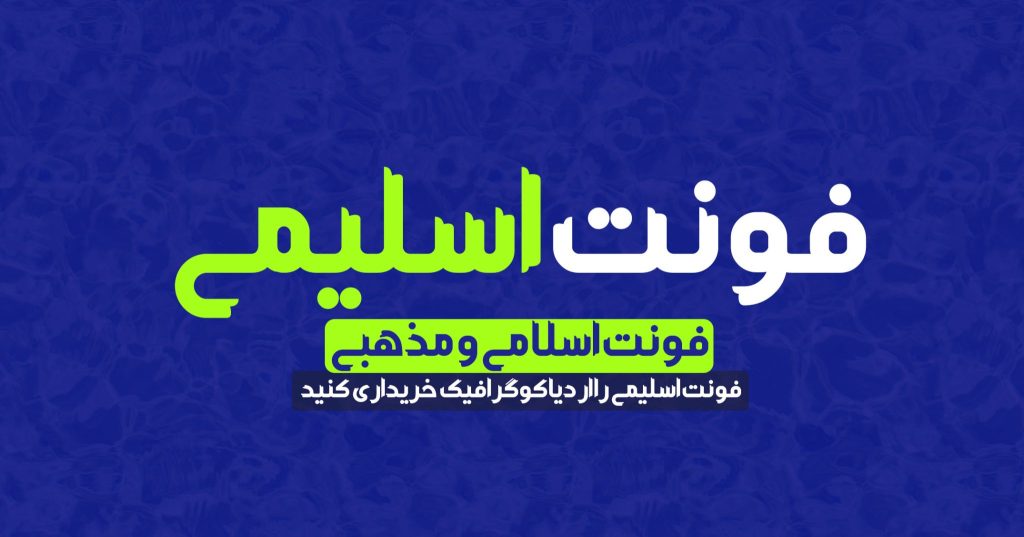
2-فونت فارسی سِریان
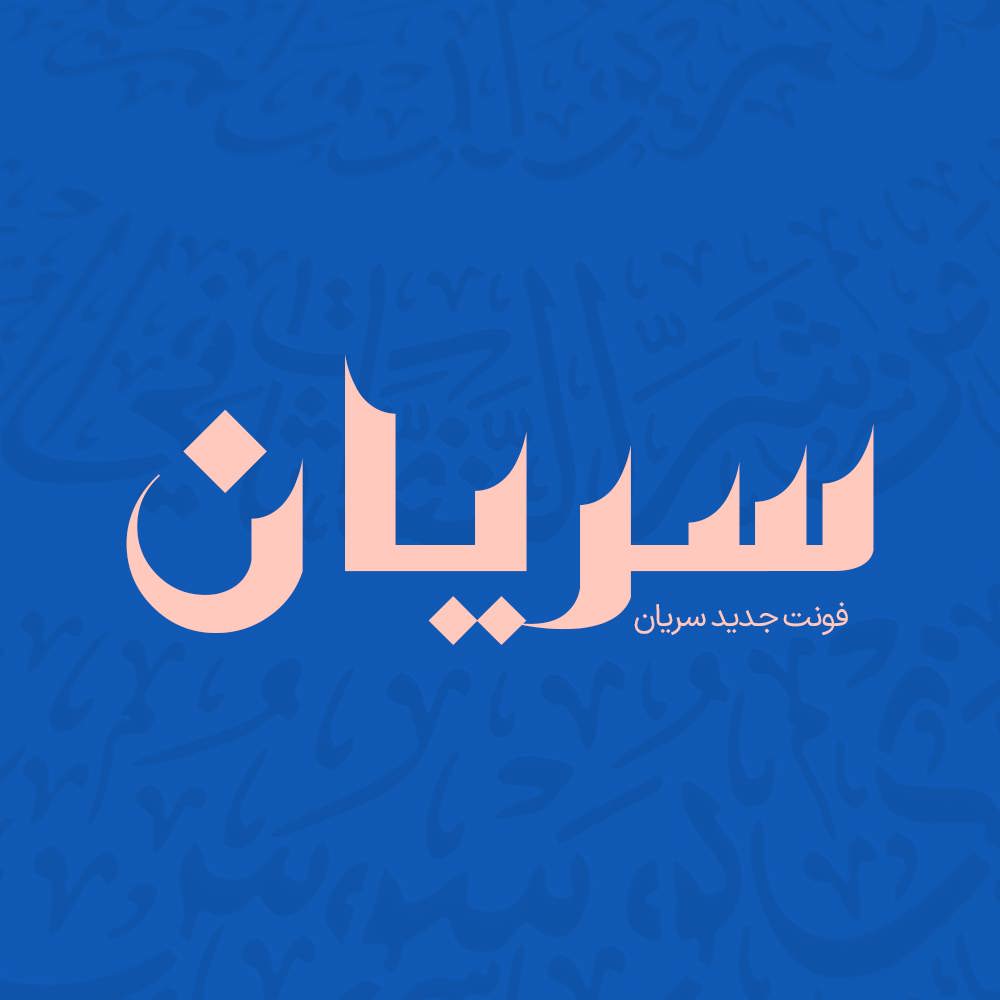
3- فونت فارسی دوران
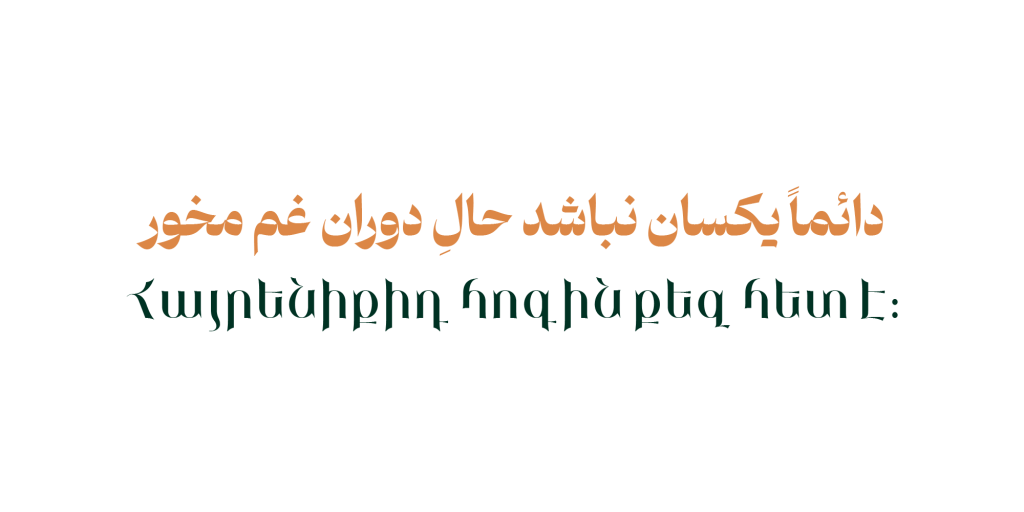
4-فونت راوی
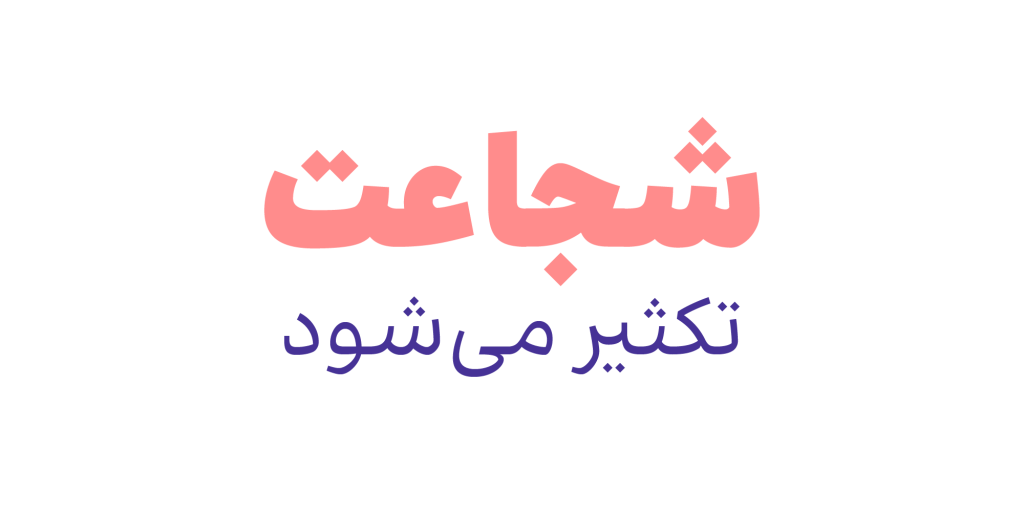
5- فونت بنیاد کودک
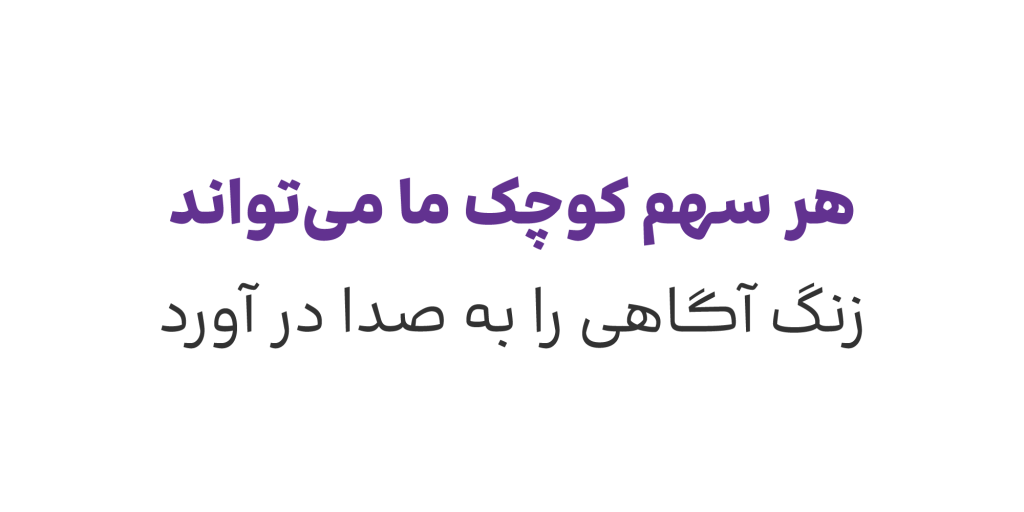
جمعبندی: طراحی مذهبی؛ پیوند هنر و معنویت
در طراحی مذهبی، فونت تنها یک ابزار انتقال پیام نیست؛ بلکه بخشی از محتوای معنوی طرح است. با انتخاب درست بهترین فونت های فارسی مذهبی، شما در حال احترام گذاشتن به چشم مخاطب و بزرگداشت آن مناسبت هستید. امیدواریم با معرفی این فونتها و استفاده از پکیجهای تخصصی، بتوانید آثار فاخرتری خلق کنید.
۴. تفاوت اصلی فونت نستعلیق با نسخ در چیست؟
نستعلیق یک خط هنری و کالیگرافیک است که بیشتر برای تیترها و جملات کوتاه کاربرد دارد، اما خط نسخ (مثل فونتهای رایج وب) برای خواندنِ متنهای طولانی و بدنهی اطلاعیهها بهینه شده است.